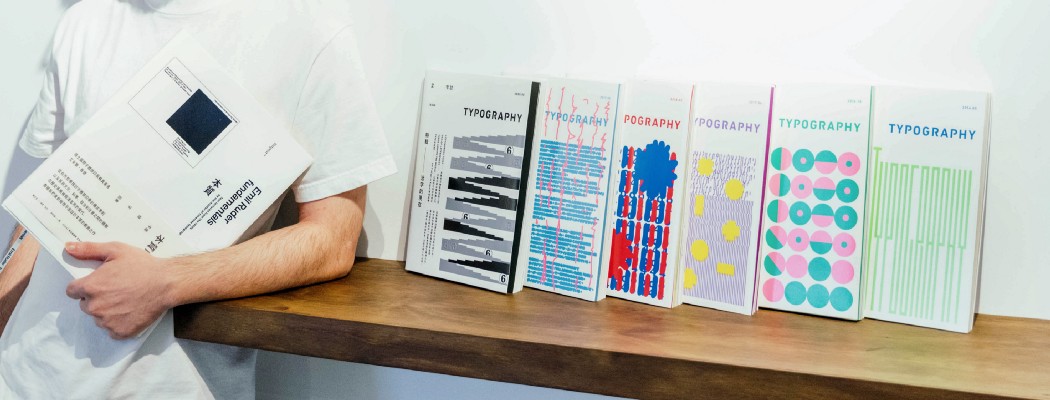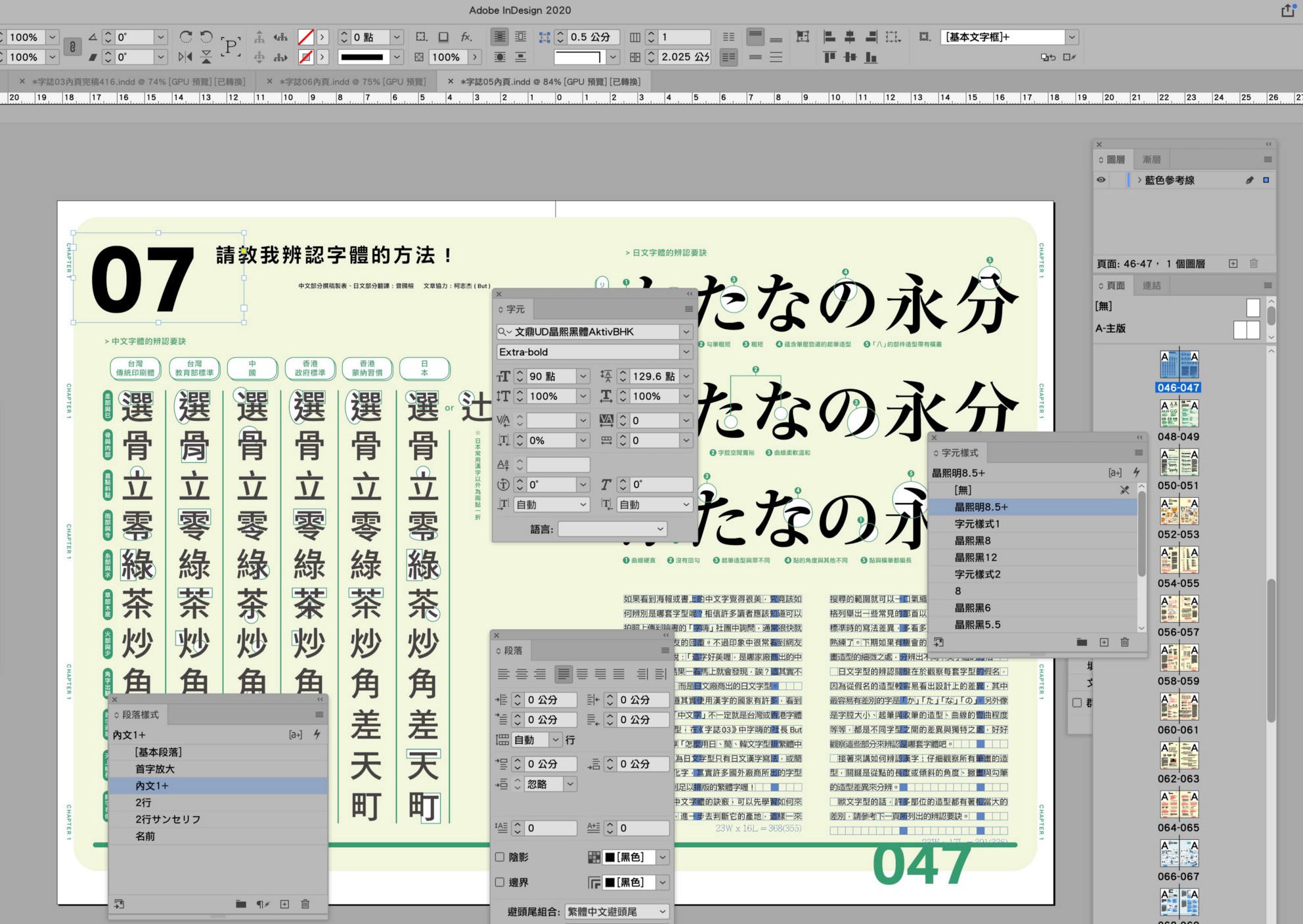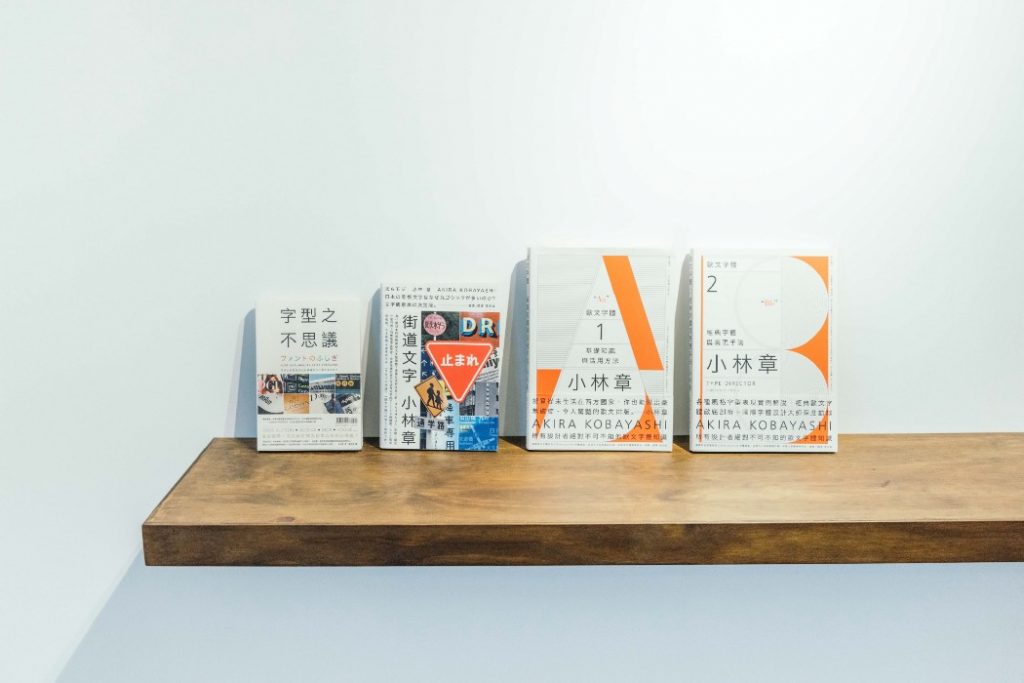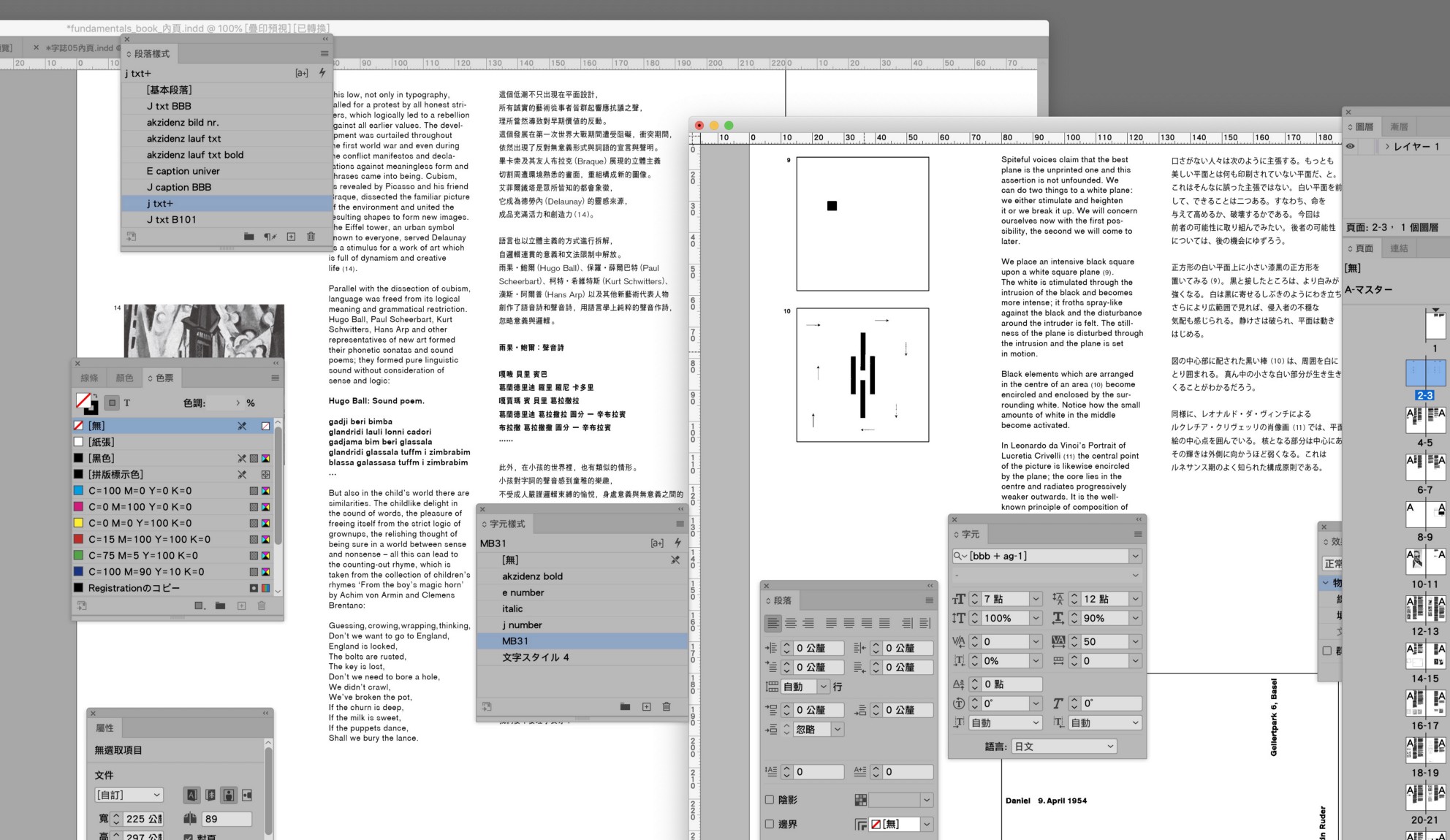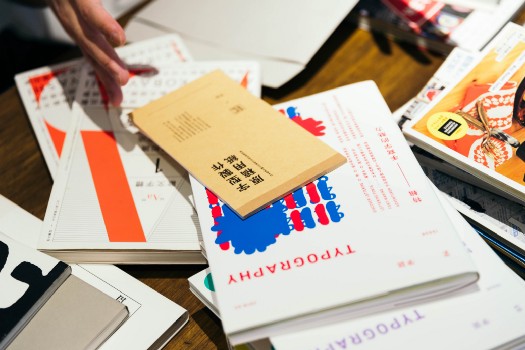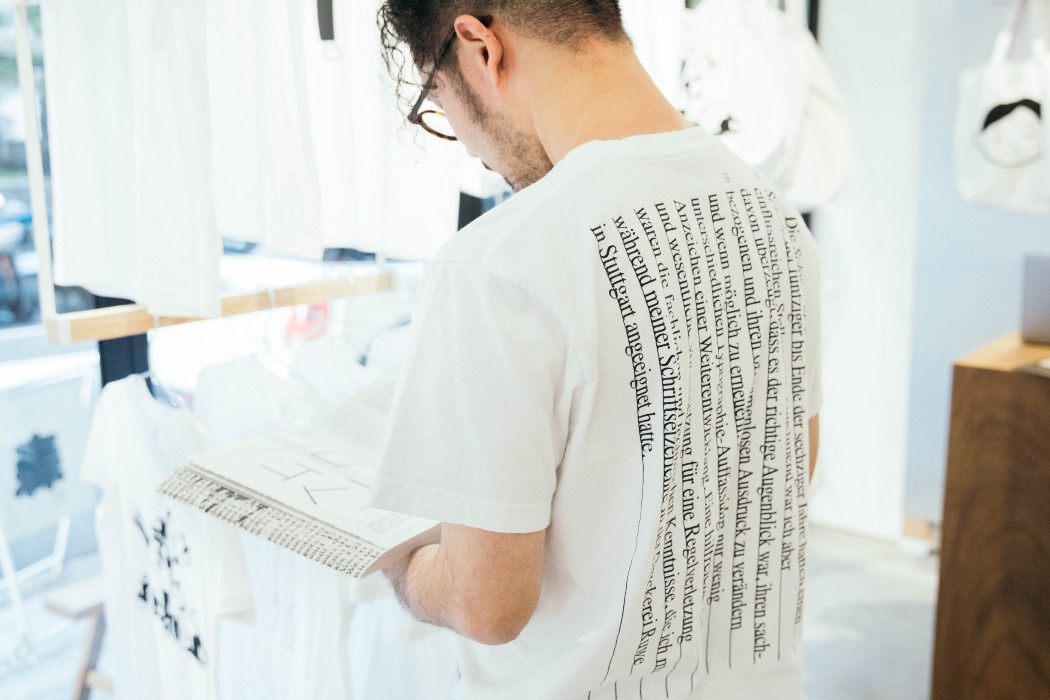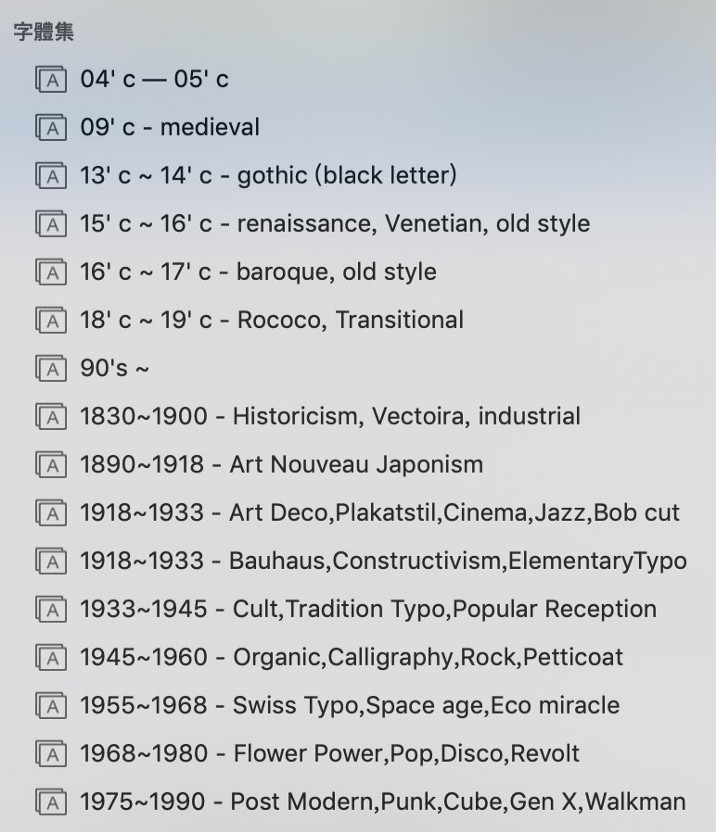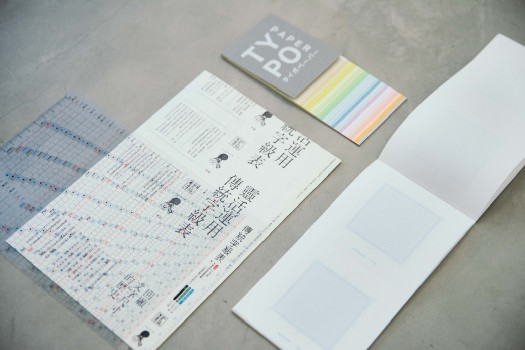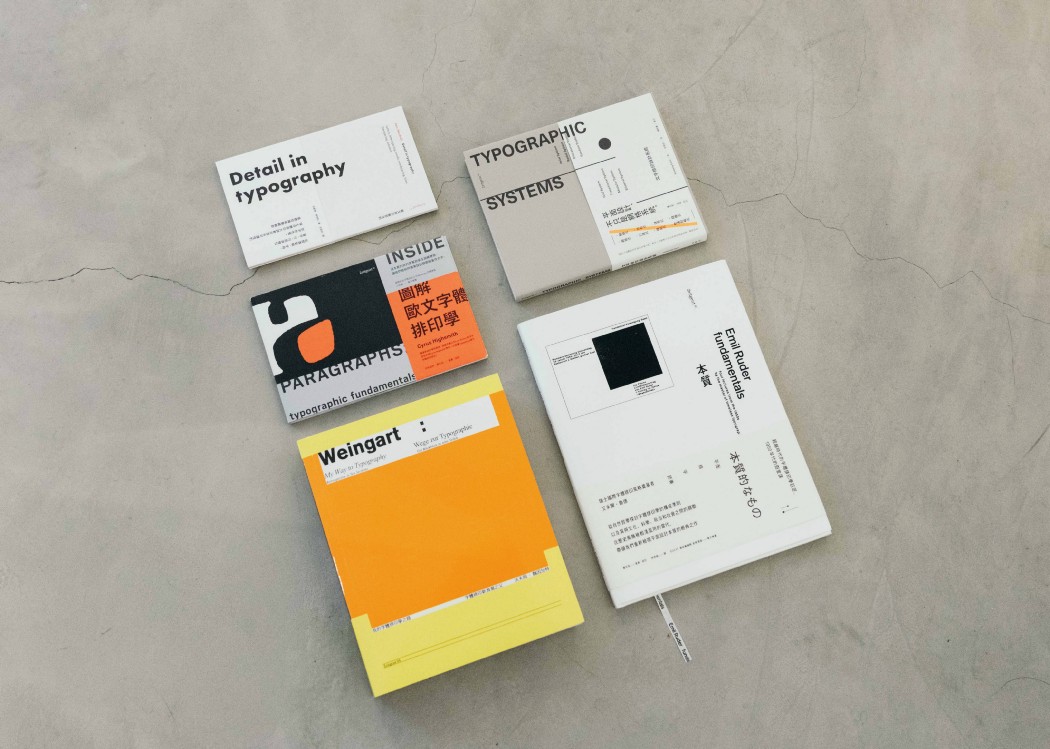
《字物 Type Matters》Vol.003 叶忠宜:从唤起到重视 催化字体探索
字体正代表着时代精神,因为文字的笔画和骨骼,会因应时代文化或地域特性而有所转变;换言之,从「字体的风格」也能看出「历史的演进」。
近年台湾设计界对于字体设计的关注度,越来越高,像自发性讨论社团林立、字体募资项目的屡屡成功、学生纷纷以字体作为毕业制作等,都可以感受得到字体逐渐受到重视。
叶忠宜更是一位不可不提及的推手之一,自2013年起,引进并翻译日本字体大师小林章的《字型之不思议》开始,他为原本平静的字体设计书市,激起了动人的涟漪,随后精选日本 Graphic 社编辑部的出版内容,结合自制内容的《Typography 字志》系列、与脸谱出版社持续企划「Zeitgeist」书系等,皆唤起大众对字体探索的重视。
一张象限图,标定与字体的缘份
叶忠宜会投入字体推广,其实是意外。他大学修习管理学院日文系,后来仅是赴日进修日文,辗转至京都造型艺术大学时,为了学习艺术摄影开始研究色彩学,并在一本书中,发现日本讨论企业识别(Corporate Identity,简称 CI ),不仅讲究颜色,亦重视字体。书里画了一张象限图,从「古典−现代」、「严肃−轻松」等四个角度剖析各种字体的风格和印象。过去攻读设计时,总只能在茫茫字体大海自行摸索的叶忠宜形容当时宛如「被触发了什么」般,这是第一次知道它们的「相对关系」。从此一头栽进其中,努力学习相关知识。学成归国后又感于台湾在这方面的讨论和研究如同沙漠,才希望把国外的资源引进来。
穿上为体排印新浪潮学派之父 Wolfgang Weingart 书籍和展览特别设计的衣服。
先锋者的三高:热血、行动和专业
在台湾要推广从未受重视的字体设计,需要的不外乎是满满的热情、超强的行动力,而叶忠宜还有第三个优势:他自己也是设计师。
例如引入《字型之不思议》时,他是直接写信给小林章本人。小林章不仅被他的直率和勇气打动,同时也以日本人的身份前往德国工作,感受到跨文化的难处和引入欧文字体观念的重要性,继而全力支持叶忠宜的想法,两人碰面后很快便谈妥授权事宜。
由叶忠宜担任企划和翻译的「小林章」系列,由王志弘设计,小林章本人也曾来台演讲。
当时小林章已经先有另外两本专业性更高的欧文字体著作《欧文字体1、2》,但叶忠宜认为要打开台湾市场,得从更大众的角度着手。《字体之不思议》原本就是集结部落格的随笔而成,由精品品牌LV、经典电影《窈窕淑女》等一般读者也会感兴趣的案例谈字体设计,简单又吸睛,相当适合「打头阵」。因为叶忠宜当时决心专心于小林章全著作的企划与翻译,于是邀请王志弘担纲中文版的设计,王又帮忙牵线脸谱出版社,最后成功让书籍问世,也有理由把小林章本人邀请来台湾演讲,顺利掀起一大波「字体旋风」。
《Typography 字志》华文世界第一本字体MOOK
制作《Typography字志》时,同样仰赖高行动力和毅力。小林章的书籍主要针对欧文,但台湾以中文为主,读者们需要更多元的养份来想象何谓字体设计。叶忠宜于是希望透过更「杂学」、也更「实时」的MOOK(Magazine+Book,发源于日本,结合书的扎实度与杂志丰富性的刊物类型)形式推广,二话不说飞去日本 Graphic 社编辑部。对方没料到竟有人单枪匹马来谈授权出版,而且不是以出版社、而是设计师个人的身份。为了取得授权,叶忠宜又飞回台湾正式成立「卵形工作室」(oval-graphic),再以该单位的名义,终于拿到签约,也打动了脸谱,一起合作出版。
目前刚出版完第六期的《Typography 字志》将会暂停出版,完成阶段性任务。
内容制作上当然也绝不马虎。考虑到能同时驾驭「翻译」和「字体」两个领域的译者不多,字体又再细分领域,所以像 Web Font(网页字型)的章节,就特别商请全台最大字型论坛「字嗨」的版主 But(柯志杰)担任翻译,因为他懂日文,有工程师背景,能精准了解此领域的用语,还可以监修哪些日文内容已经不合时宜。翻译日本字游工房创办人暨设计大师鸟海修的文章时,则由曾当过他学生、字体设计师的曾国榕来执行,原汁原味重现老师的口吻。
至于中文内容,光是字体选择便大有学问。《Typography 字志》选用的是「文鼎晶熙黑体」,此字体具备「通用设计」(Universal Design,简称UD)的概念,亦即「同时顾及大众及弱势者的需求为出发点」。关键在于,以中文字而言,其由各笔划所包围出的字腔较大,或用书法的九宫格来想象,各笔划都远离最中间那格「中宫」,呈现出「中宫放松」(而非中宫紧凑)的状态。在这种情况下,即便字级相同,视觉上也会看起来更大,因此就算放成小字可读性也高。然而应用在生活上,也适合做为交通指示用字,或利于视力不便者辨识。
叶忠宜编排《Typography 字志》内文的工作画面。(卵形提供)
《Typography 字志》选用的「文鼎晶熙黑体」具有中宫放松的特性,就算放成小字可读性也高。
为了把这些珍贵的内容传递出去吸引读者买单,叶忠宜替杂志规划的赠品找来了具有影响力的设计师来帮忙,像是力邀聂永真、王志弘、瑞士设计师 Michael Renner、韩国设计教父安尚秀,以及日本手绘字书籍装帧大师平野甲贺,来替刊物设计附赠海报,像第三期《严选字型 401》,还附赠日本百年字体公司森泽(MORISAWA)和祖父江慎授权的字级表,美观又实用,进一步说服更多读者掏出荷包。
更经典、更扎实的知识累积
有了小林章的深入浅出,又有宛如懒人包般的MOOK创造话题,下一步,就是朝更专业的知识迈进。叶忠宜再度和脸谱携手,企划名为「Zeitgeist」的书系。「Zeitgeist」在德语有「时代精神」的意思,叶认为字体正代表着时代精神,因为文字的笔画和骨骼,会因应时代文化或地域特性而有所转变;换言之,从「字体的风格」也能看出「历史的演进」。
由叶忠宜担任主编和设计的「Zeitgeist」书系。
秉持这份信念,此书系朝两大方向进行选书:一是在全球设计界都产生巨大影响、台湾却从未引进的大师经典,例如以 20 世纪 最伟大的 瑞士 字体排印曁平面设计教育家 Emil Ruder 的《本质》 和字体排印新浪潮学派之父 Wolfgang Weingart 的《我的字体排印之路:沃夫冈‧魏因加特》,是从文化、科学、政治、社会等宏观视角与随社会变迁的成长脉络来谈论排印形成的原理;二是知识型、工具型的技术养成类书,例如《图解欧文字体排印学》、 《文字排印设计系统》、《欧文排印细部法则》等 ,用诸多实例分析各种字体、字级、字距、 排版的变化效果,让读者能进一步学习并实作 。
《本质》排版画面。(卵形提供)
作为书系的主编兼设计,叶忠宜展现出对细节的坚持。像他很在乎翻译,若发现编译出来的文字不顺,会先和同样熟悉日文的责任编辑、同时也是脸谱副总编辑的谢至平讨论,还有疑惑就跑去找日文版做二次确认。「因为日本人翻译很强,很多翻译书也都有日文版,所以如果发现哪边怪怪的,我会找日文版,再对照原文。」叶忠宜笑道:「应该很少设计师烦人又刁钻吧!」
而筹备过程中,也有令他大感惊喜的时刻:由于书籍原文版本通常都是由大师操刀设计,因此收到原文版的 InDesign 编排档案时,他就能亲眼一窥「大师的设定」。例如像《本质》,无论原文或日文版,都由知名瑞士设计师 Helmut Schmid 设计排版。每一个字体的大小、每一个符号往上几单位,都能全部摊开。像 Schmid 因为思考如何让日文完美匹配原文的视觉阅读性,会将特别选定的日文字体再进行微幅的伸缩调整,如此叶忠宜就会知道 Schmid 要的点是什么。
即便「内容」一致,译本却几乎是得重新来过的大工程。叶忠宜往往得至少思考两天才能正式着手,后续反复修改、校正更不在话下。他也很感谢从小林章的书就开始合作至今的最大工程 — — 编辑谢至平。「至平的校稿与作业超细心 ,是超典型处女座的完美主义者。 」谢至平则笑道:「『坚持』是忠宜的正字标记,很不容易妥协。但他现在已经比起四、五年前认识时要和缓很多。」编辑和设计一样,都是一门手工艺,得无数次和细节较劲,但也因此才能产出优秀的成品。
脸谱副总编辑:谢至平(左);叶忠宜(右)
谢至平表示,由于「Zeitgeist」并非封闭型的书系,会一直执行下去,并依照授权谈定的顺序出版。以目前一年二至三本的出书速度,手边的书单存量至少已备齐5年以上的出版量,有兴趣的读者绝对可以拭目以待。
「字体」就是我的收藏品
推广字体的心愿逐渐落实了,但叶忠宜并未忘记除了推广以外,自己身为设计师该做的功课。翻开计算机里的字体簿,里头有学生时期一直到现在,花费重金「收藏」的各种字体,还依照年代、大师、国家等不同项目进行分类。最近则是爱上搜集2015年以后,国外冷门小型公司出的字体,「因为他们可以很外放,做出大家少见大胆且破格,但又好用的作品。」
叶忠宜的字体库宛如编年排列的百科全书一般。(卵形提供)
换言之,对于设计相当坚持的叶忠宜,在字体寻找的路途上依然不停歇。像是中文的使用,他特别讲究内文字体需要的工艺性,因此还尚未发现心目中完美的中文内文字体,因此他通常会先选择高规(汉字量较多)的日文字体,阙漏字再自己补上,甚至标点符号、数字都会混用超过一个字体,以及不同的版面设定,来构成最想呈现的版面。他特别举例,像是字游工房出品的「游黑体」就是他常用的字体之一。「虽然有 Apple 内建,但仅有字重版本『 Regular 』和『 Bold 』,若要用这字体排中文,则是位于这中间的 Demibold 版本最好用 , 但必须另外购买 。 超贼的!最好用的东西都得另外购买。 」
Profile/叶忠宜 Yeh Chung-Yi
1982年生,2007 年赴日,最后攻读京都造形艺术大学研究所毕业,2015年成立「卵形 oval-graphic」设计工作室,透过企划出版,大力推广字体设计。本身是平面设计师,主要作品包含《 Typography 字志》和「Zeitgeist」书系设计,2018年国庆节主视觉等。2018年秋天又和格式设计的王耀邦以及WISDOM®主理人齐振涵,合作打造实验性场域「森³ sunsunmuseum」。目前工作及居住于台北。